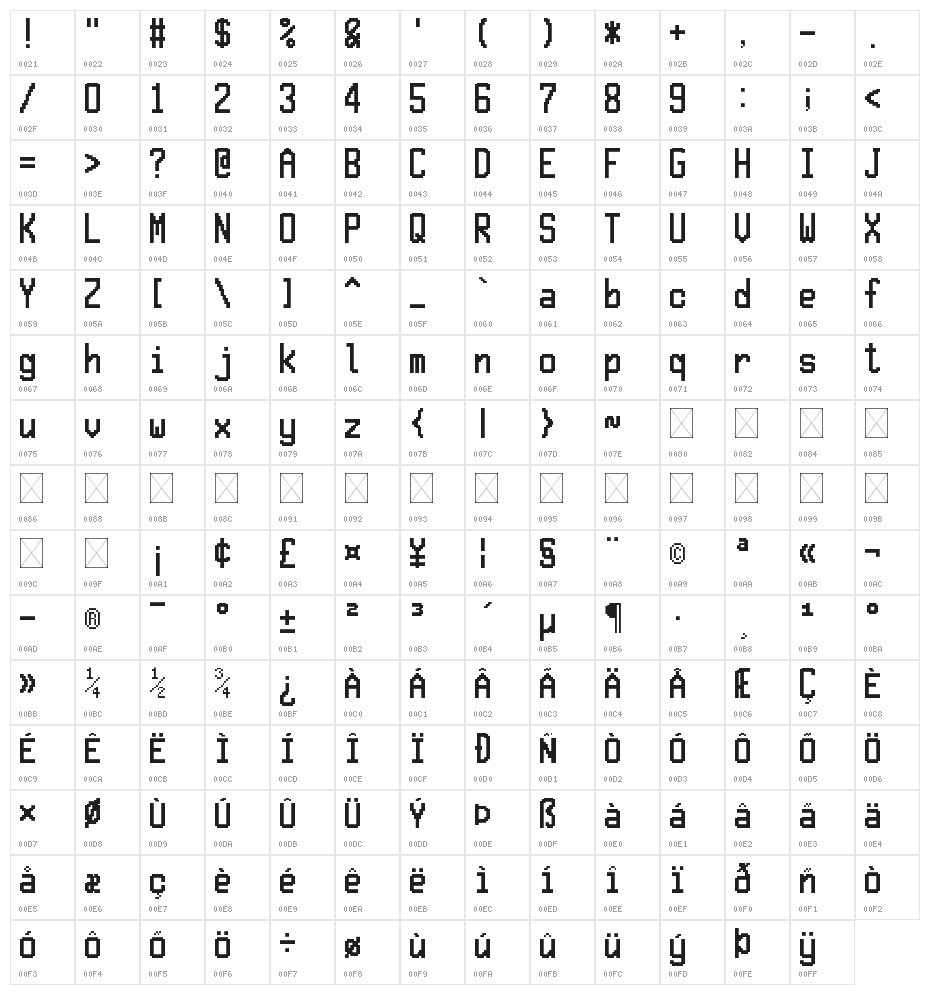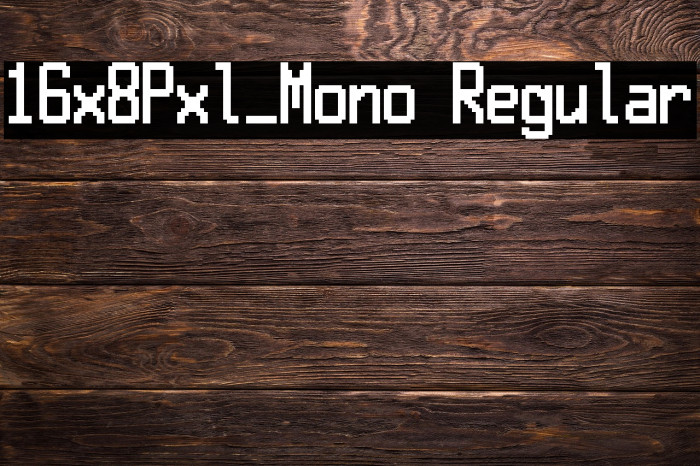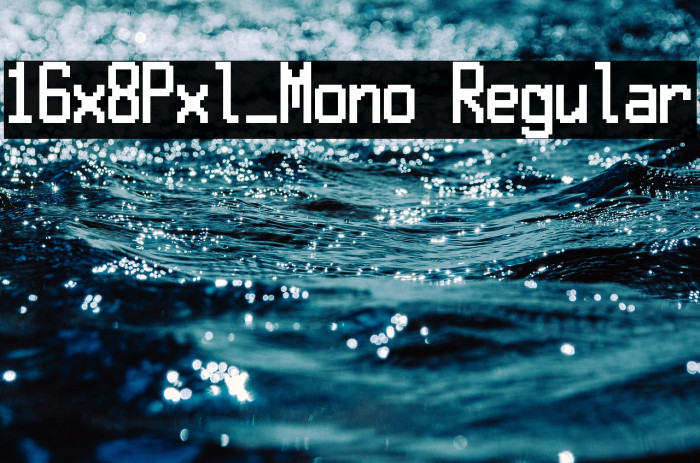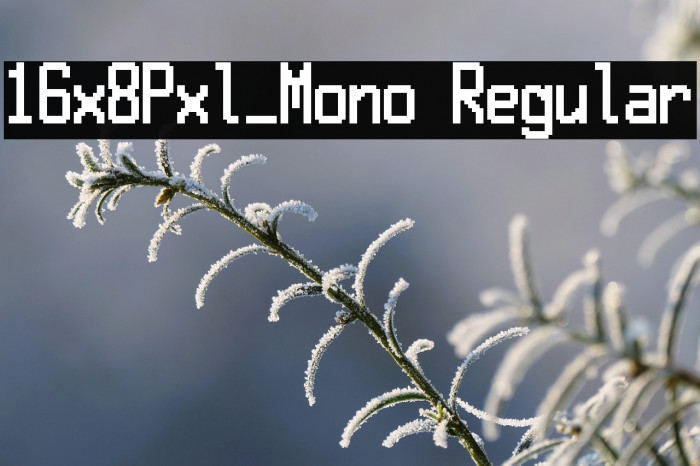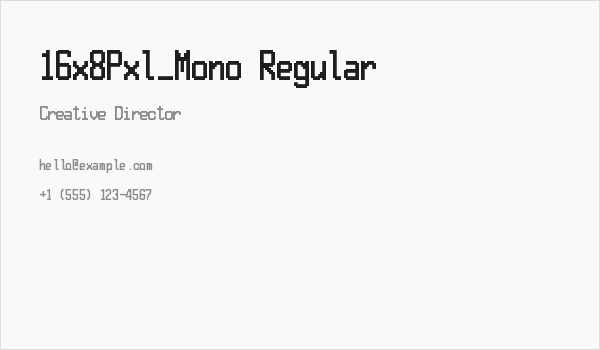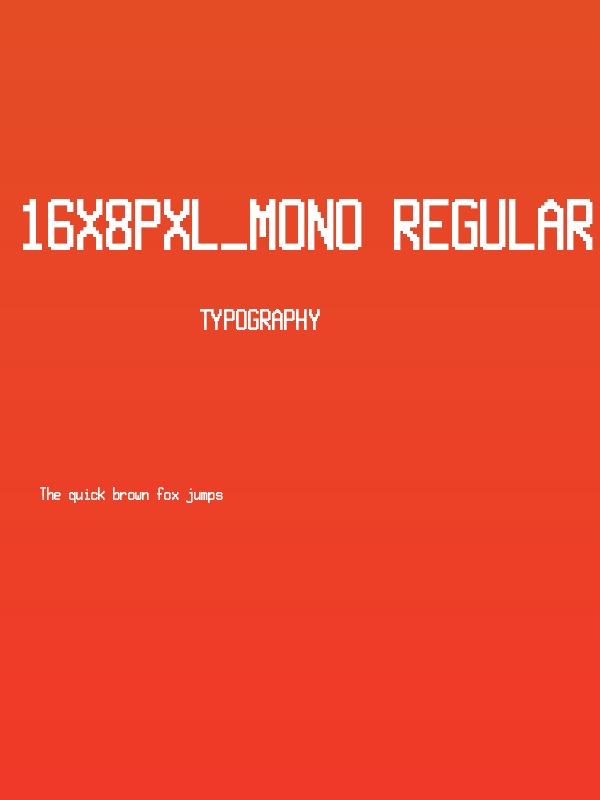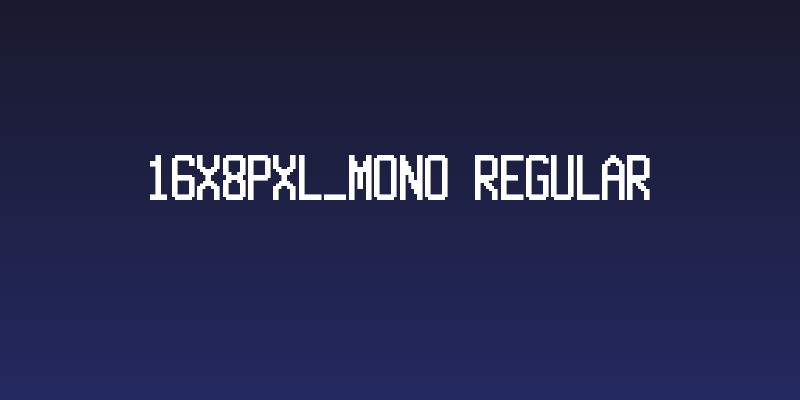
16x8Pxl_Mono Regular Font
| Stile generale | Retro |
| Caso d'uso | Headlines, Digital displays, Coding interfaces |
| Progetti proposti | Ideal for retro-themed designs, video game graphics, digital art projects, and coding interfaces. |